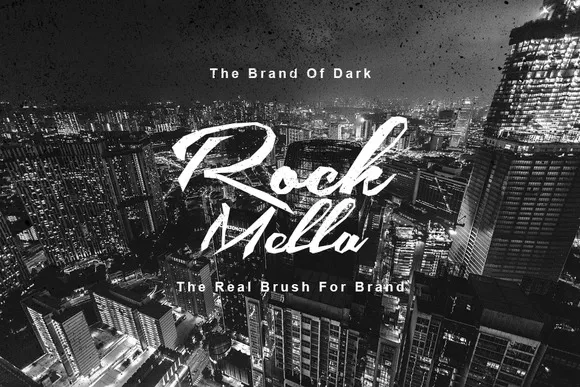
Rock Mella Brush Font – Download Grátis
Introduzimos a Rock Mella Brush Font! Desenhada por Ferdiansyah_ijemrockart, esta é uma fonte premium vendida na Creativemarket, que agora pode ser baixada de graça. A Rock Mella é um marcador feito à mão com estilo moderno criado para atender às necessidades dos seus próximos projetos de design. Esta fonte foi concebida como um marcador de mão dura e tem uma aparência moderna, perfeitamente adequada para diferentes finalidades. Use-a em títulos, logos, cartas pessoais, selos, placas, folhetos, panfletos, selos, camisetas personalizadas, entre outros usos. Com a Rock Mella Brush Font, você terá uma variedade de opções para dar um toque único e diferenciado aos seus projetos gráficos. Sem dúvida, é uma fonte perfeita para aqueles que procuram algo com uma aparência artesanal mas que ainda mantém a funcionalidade moderna necessária para os desafios futuros do design.